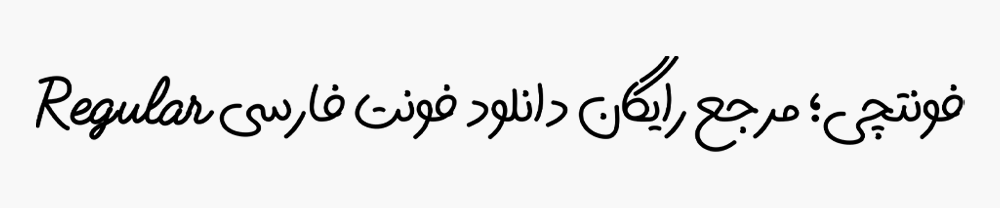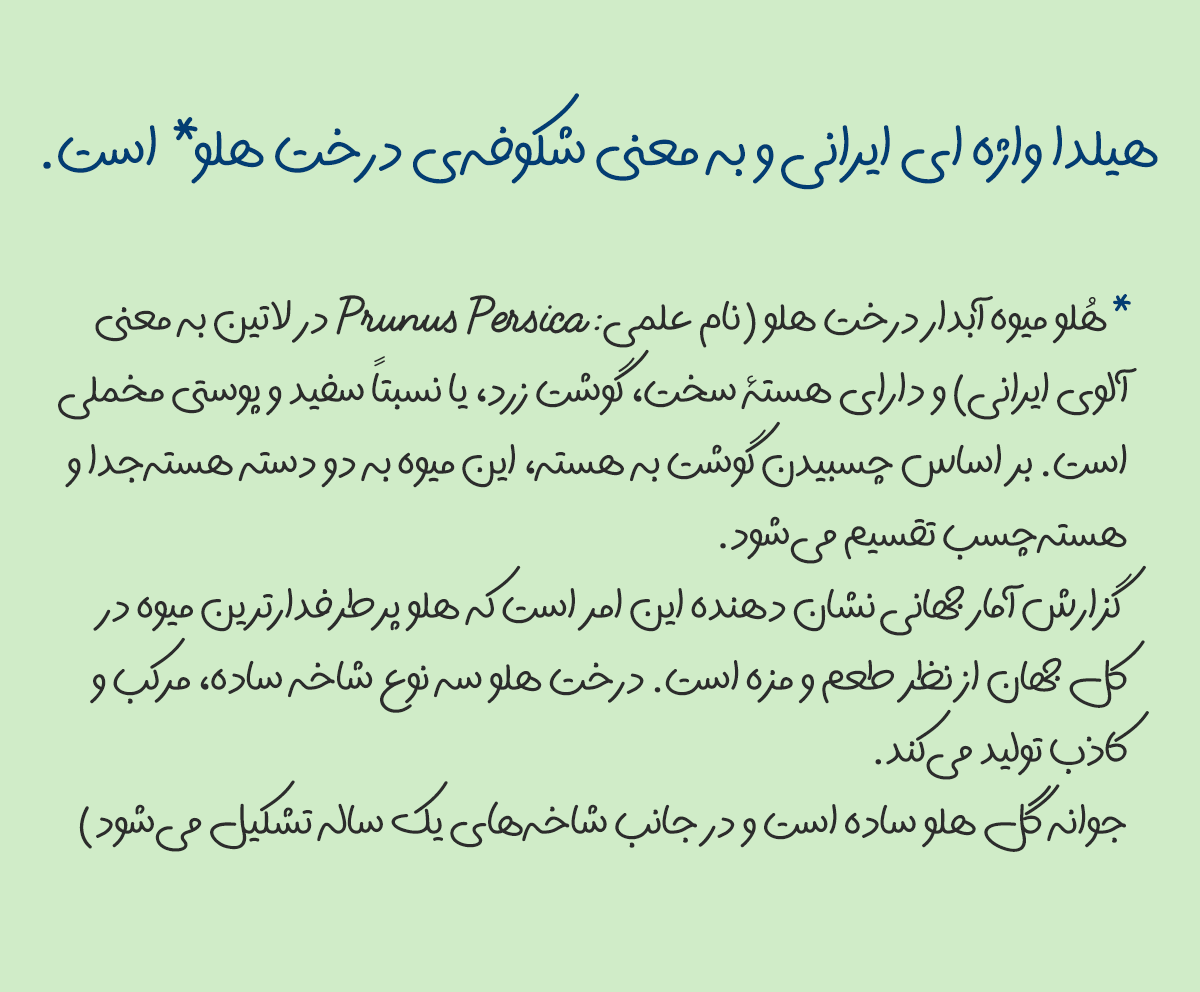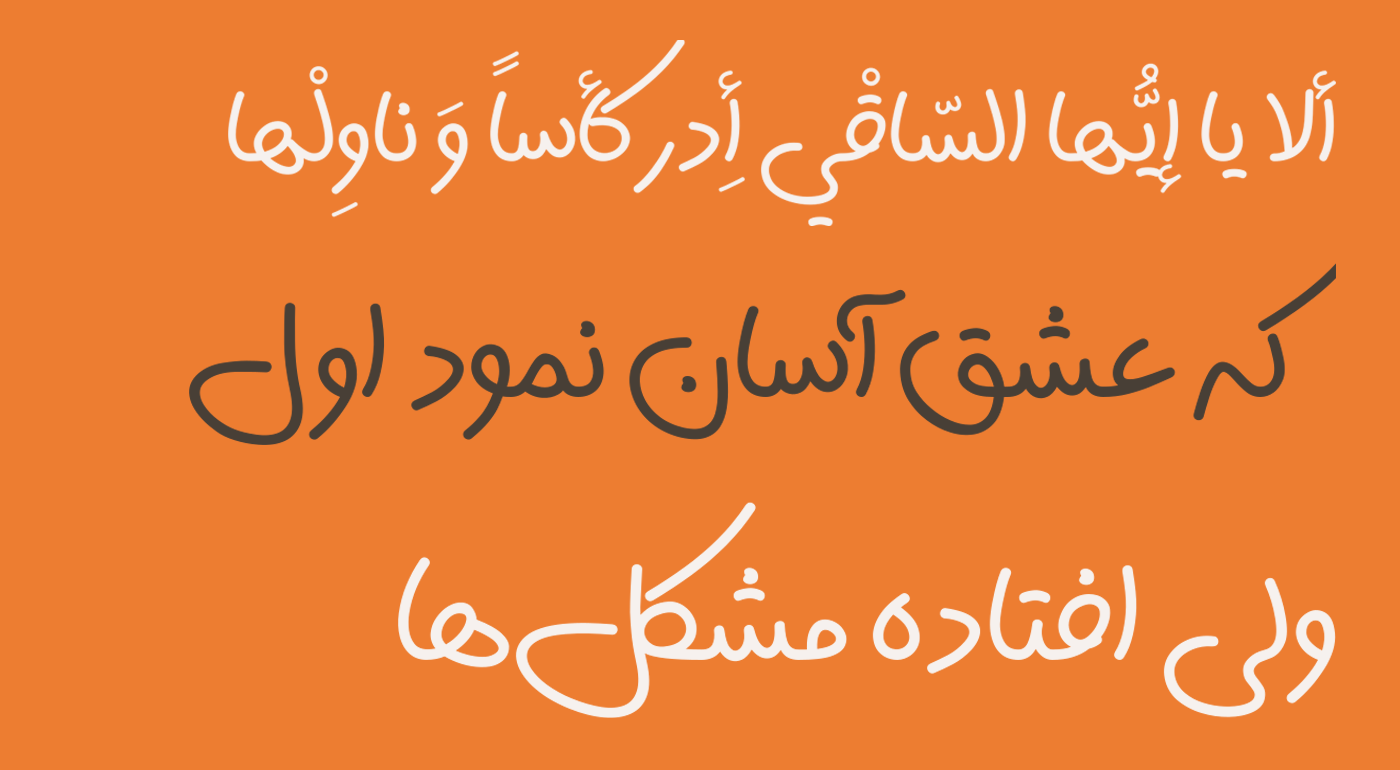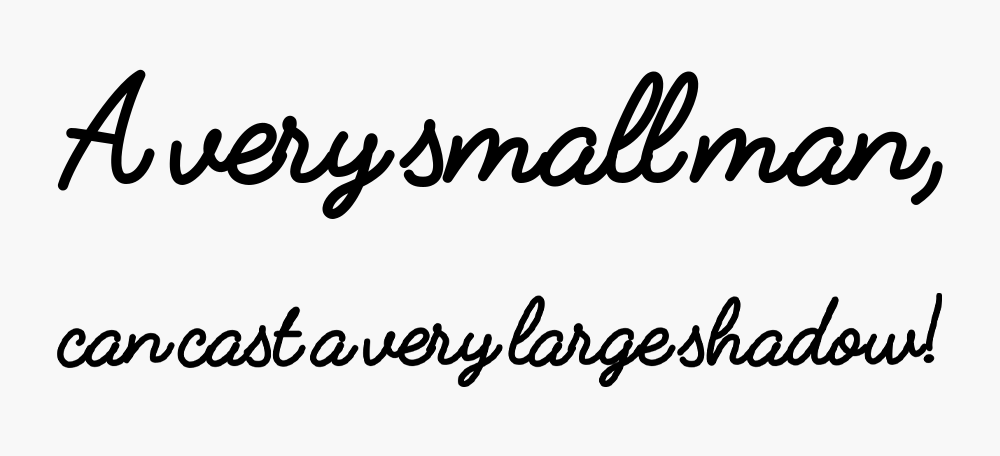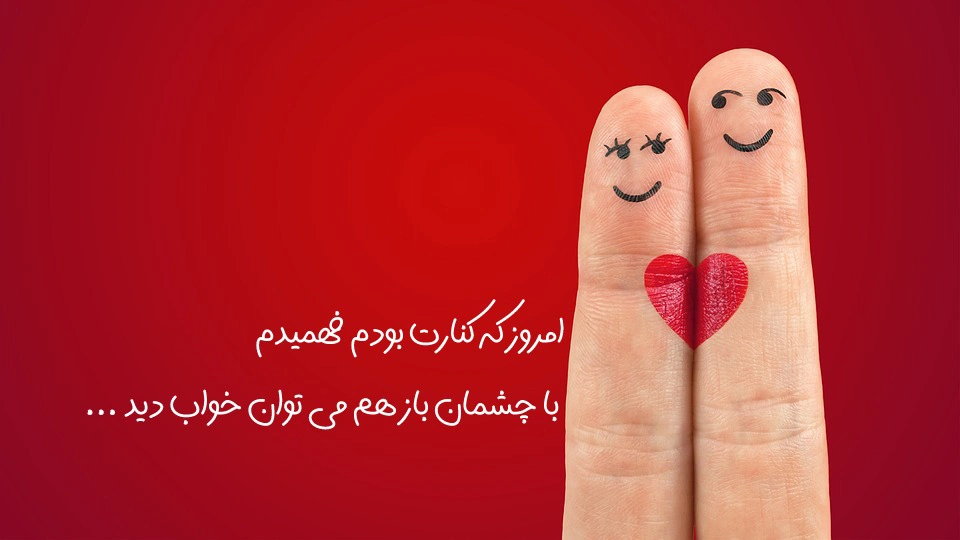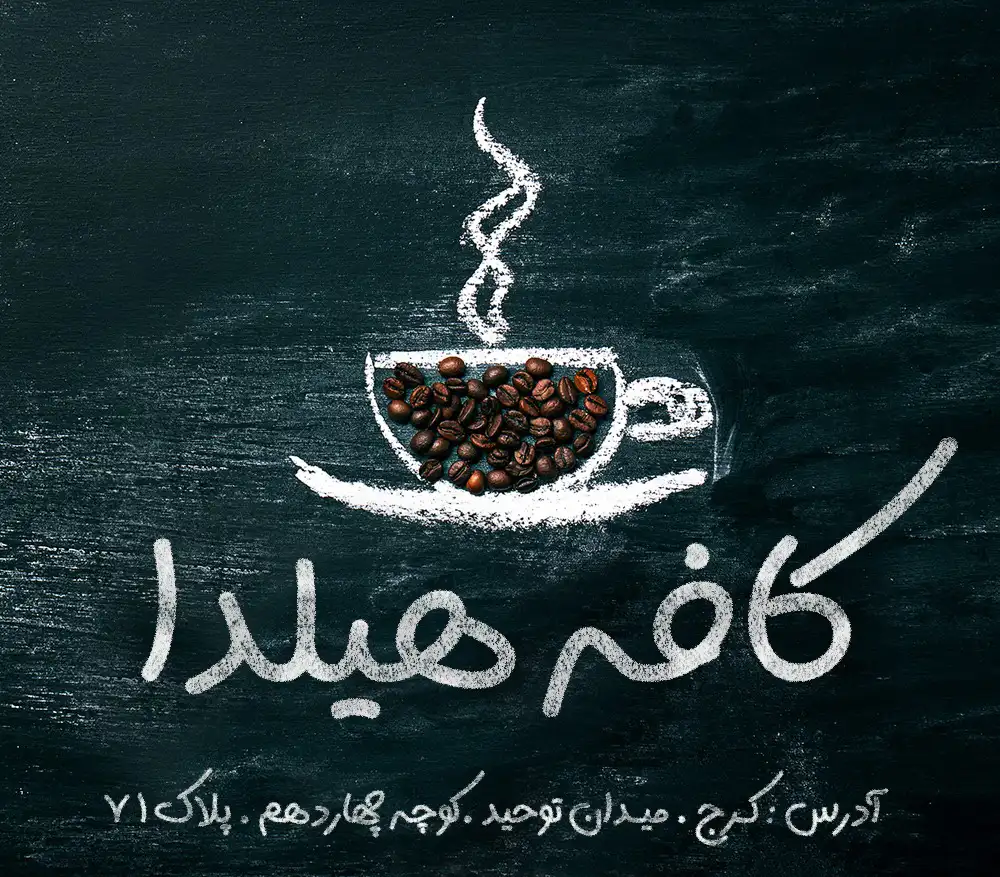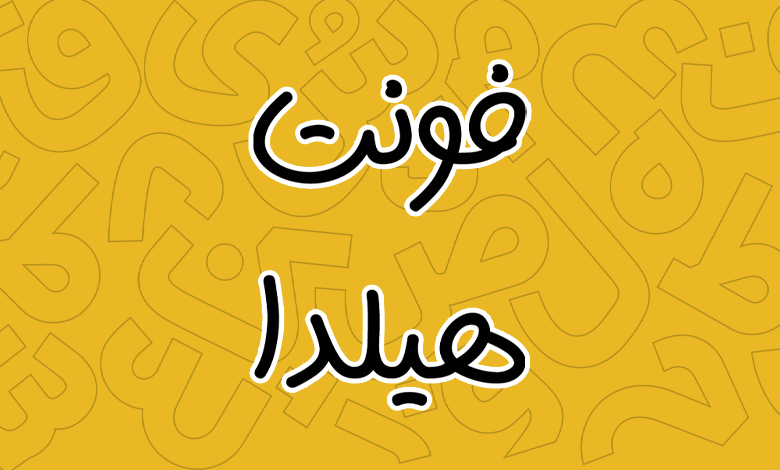
فونت هیلدا (Hilda)
فونت هیلدا (به انگلیسی: Hilda) یک قلم دستنویس با ساختاری کاملا ساده و بهدور از کنتراست با ضخامت است که میتوان از این قلم در متنهای کوتاه تا بلند و حوزه تبلیغات استفاده کرد. در این قلم دست نویس حروف کاملا ساده و کنترل شده طراحی شده و به دور از هر گونه اغراق برای تبدیل شدن به یک فونت فانتزی هستند.
در واقع این قلم بر اساس دستخط شخصی محمد عموئی توسط وی ساخته شده است که پیش از این یک قلم دستنویس دیگر با نام فونت مانلی را در کارنامه خود دارد. نسبت به آن قلم سادهتر، ضخامت کمتر و فاقد کنتراست از نظر ضخامت (کم و زیاد شدن ضخامت در حروف) است.
در ادامه این نوشته از سایت فونتچی به نقد و بررسی کامل فونت دست نویس هیلدا خواهیم پرداخت؛ قلمی که میتوانید برای طراحی انواع پوستر و عکس نوشته در شبکههای اجتماعی از آن استفاده کرده یا اینکه در حوزه تبلیغات، خصوصا تبلیغات کودک و نوجوان که این قلم ساختاری نرم و کاملا دوستانه دارد بهره ببرید.
بررسی و دانلود فونت هیلدا (Hilda)
حروف در فونت هیلدا به طور کنترل شدهای رها هستند. نه آنقدر زیاد که نتیجه یک فونت فانتزی و اغراق شده باشد؛ و نه آنقدر حساب شده که تبدیل به یک قلم متن ساده شود.
سبک طراحی و وزن فونت هیلدا
فونت هیلدا بر اساس دستخط شخصی طراح ساخته شده است و مناسب استفاده برای متنهای کوتاه تا بلند است. این قلم دارای خوانایی مناسبی بوده و در تمامی حروف نقاط، خمیدگیها، چشمها و دندانهها دارای ساختاری نرم و دوست داشتنی هستند.
حروف دارای ضخامت یکسان هستند که به چنین سبکی مونو لاین گفته میشود و فاقد کنتراست است. اما با این حال این قلم چه در اندازههای کوچک و چه بزرگ خود را بهخوبی نشان میدهد. استفاده از این فونت دست نویس با اندازه بزرگ ظاهری شارپتر خواهد داشت.
پشتیبانی از زبان عربی و انگلیسی
فونت دست نویس فارسی هیلدا جدا از این زبان، از زبان عربی و انگلیسی هم پشتیبانی میکند. در هر دو این زبانها ساختار فونت بر همان سبک دستنویسی تکیه دارد که در فارسی آن را میبینیم.
پشتیبانی آن از عربی کامل بوده و جدای از اعراب و کاراکترهای خاص، اعداد «۴۵۶» که در مقایسه با اعداد فارسی «۴۵۶» ظاهر متفاوتی دارند رعایت شده است. همچنین اعراب به درستی در جای خود قرار میگیرند و طوری نیست که در تصاد با هم باشند.
در نسخه انگلیسی این قلم نیز همان سبک طراحی دست نویس بر مبنای فارسی پیاده سازی شده است. حروف ساختاری نرم داشته و مملو از منحنیها و کشیدگیهایی تزئینی در برخی حروف مثل «A, Y, L, T» هستند که بهنوعی متصل کننده به حرف بعدی هم در برخی موارد به حساب میآیند.
مناسب طراحی انواع پوستر و تبلیغات
از این قلم میتوانید برای طراحی انواع پوستر جهت اشتراک گذاری در شبکههای اجتماعی یا بنرهای محیطی استفاده کنید که در زیر نمونههای از آن را مشاهده میکنید.
جدیدترین نسخه فونت هیلدا ورژن ۱.۰ است که در آذر ۱۴۰۱ منتشر شده است. در این نسخه از قلم فعلا خبری از حروف و ترکیبات جایگزین وجود ندارد و انتظار میرود که با آپدیت بعدی در نسخه بالاتر چنین ترکیباتی به آن اضافه گردد.